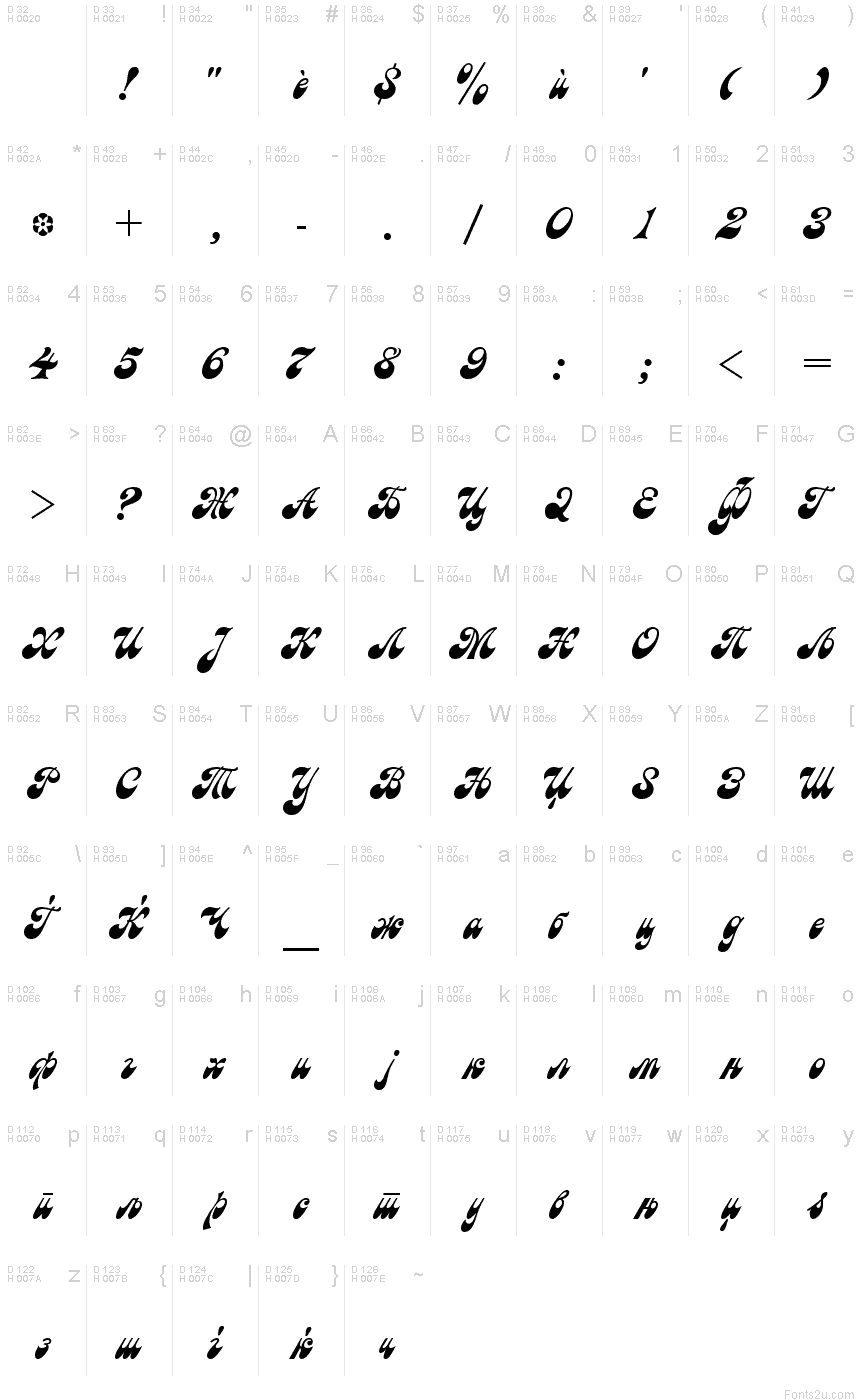
Progettato nel 1998 da Marijanco Galevski, Macedonian Astra è un font cirillico gratuito di stile calligrafico, caratterizzato da una silhouette corsiva sinuosa e tratti arrotondati. Il suo ritmo nasce dalla ripetizione di anelli e raccordi fluidi, che mantengono costante il flusso delle lettere lungo tutta la parola.
Macedonian Astra è perfetto per partecipazioni di nozze, certificati, loghi di boutique, biglietti d'auguri, titoli di poster e monogrammi: ideale ovunque una riga breve richieda una scrittura elegante e dotata di un movimento netto. Le sue forme fluide portano un tocco personale e una dinamicità tale da valorizzare un nome o un saluto in modo naturale e pulito, senza bisogno di decorazioni superflue.